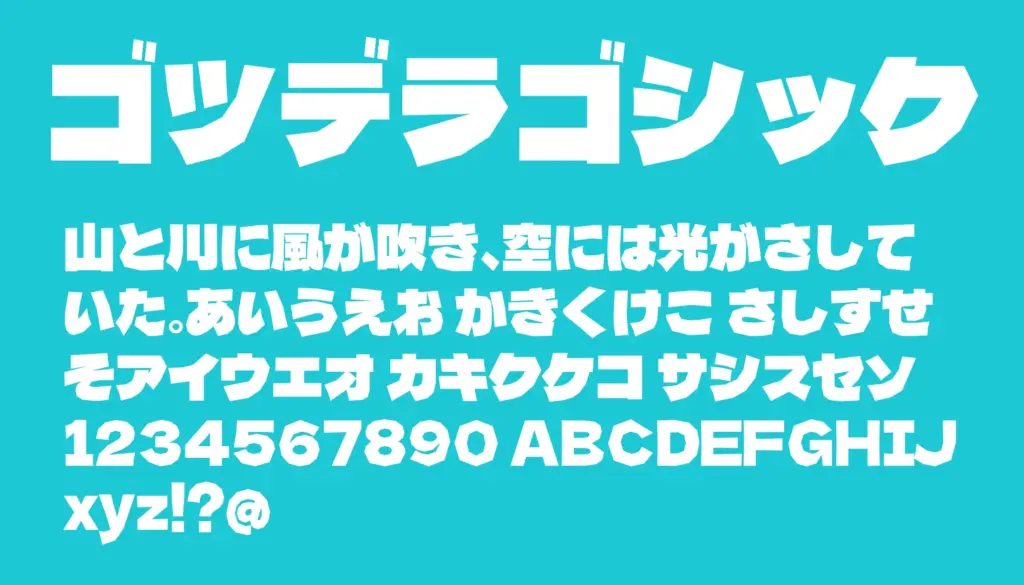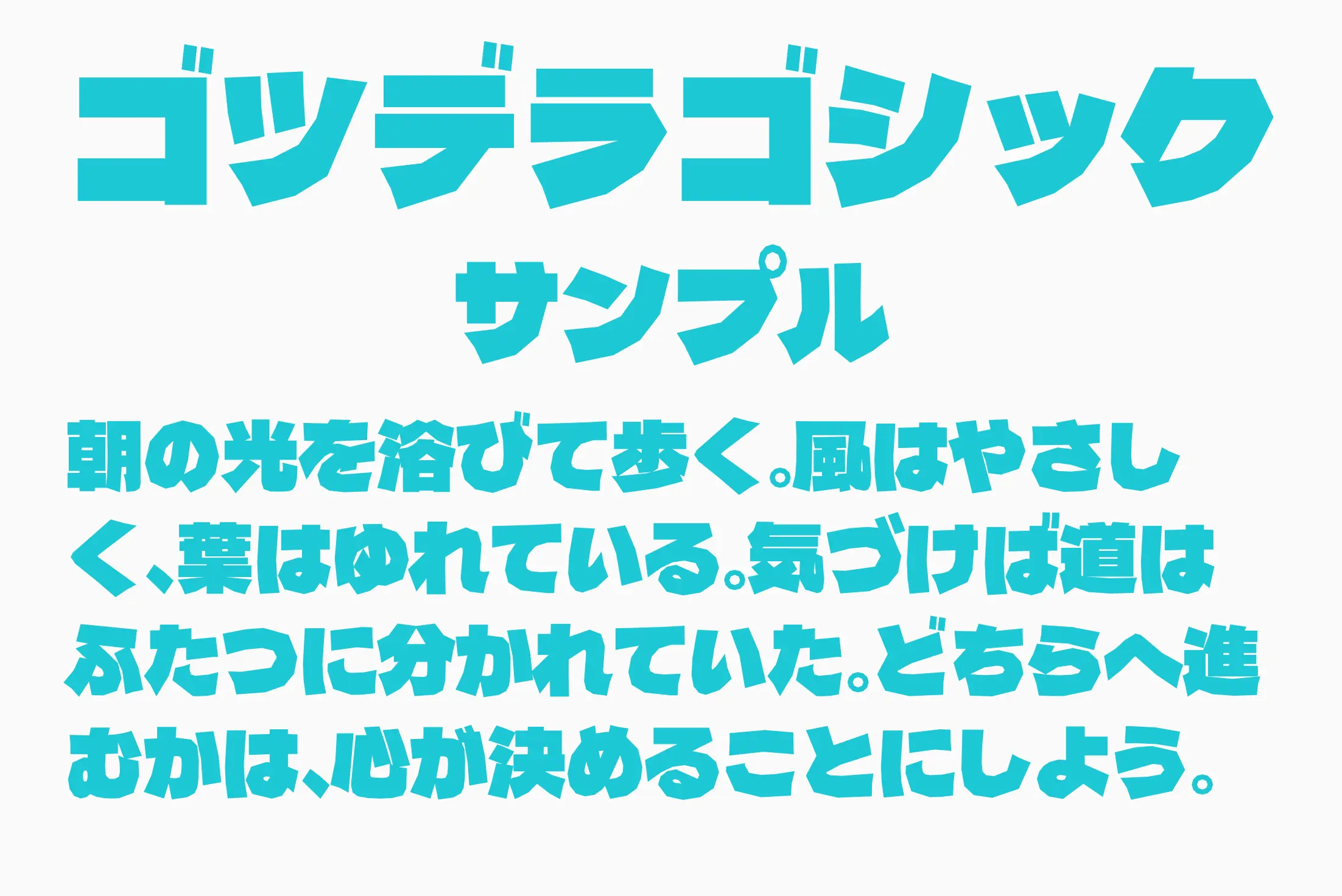
Dela Gothic One をベースにした極太ゴシックフォントで、ごつごつとした質感が特徴です。豊富な文字セットが揃い、商用利用にも対応。タイトルやロゴ、サムネイル、動画テキストなど視覚インパクトを重視する用途に最適です。繊細さや可愛さより、力強く目立つ表現を求める場面で活躍します。
ゴツデラゴシック